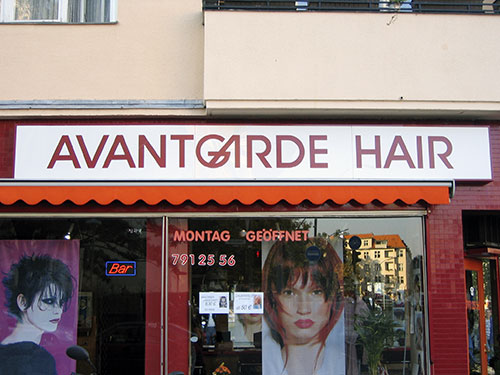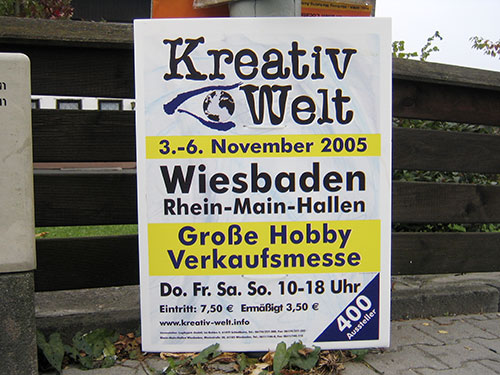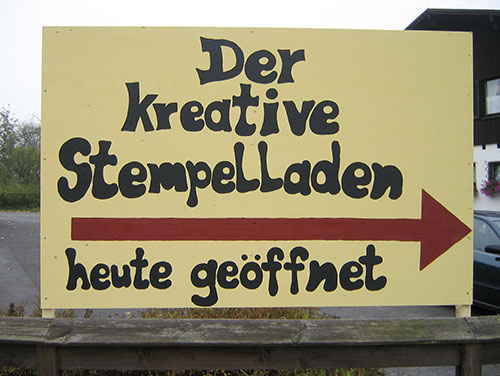
Fontnaepfchen 4: kreativ seinWenn Sie professionell gestalten, verwenden Sie nie das Wort
»kreativ« für Ihre Arbeit. Warum, werde ich gleich zeigen.
Der Begriff steht bei mir seit Jahren auf der schwarzen Liste. Inzwischen ist er
ganz unten angekommen: Bastelstuben sind kreativ, Frisöre, Plattenleger,
Stempelläden ... ja in Wiesbaden gibt es Anfang November sogar die Messe
»Kreativ Welt«. Die Werbung dafür lässt ahnen, was zu
![]() Beim Wochenendbesuch in meiner Heimatstadt traf ich auf zwei Schilder, die
nur wenige Meter voneinander entfernt am Ortsausgang standen. Das eine verweist
auf einen »kreativen Stempelladen« – ich wusste noch gar nicht,
dass inzwischen schon Läden kreativ sein können. Gleich daneben wird
die Fachmesse für die Betreiber solcher Einrichtungen angekündigt:
Kreativ
Welt in Wiesbaden, vom 3. bis 6. November in der Rhein-Main-Halle. In
beiden Fällen entlarvt die Typografie das Anliegen, oder anders herum: sie
bestätigt den Stellenwert des Wortes »kreativ«. Es ist
ausgebrannt, am
Ende.
![]() Bad Camberg, Oktober 2005 (Foto: Fontblog) ![]() Wenn Kreativität die Hobby-Welt erreicht ... (Foto: Fontblog) ![]() Ed Benguiat sagte mal, dass sich mit der Schrift Avantgarde eigentlich nur eines richtig ansprechend schreiben ließe: das Wort Avantgarde (siehe hier ). Doch auch dies gelingt nicht immer, wie ich gestern in Berlin Steglitz lernen musste ... (Foto: Fontblog) Herausgegeben: Mi - Oktober 12, 2005 at 08:59 vorm. | |